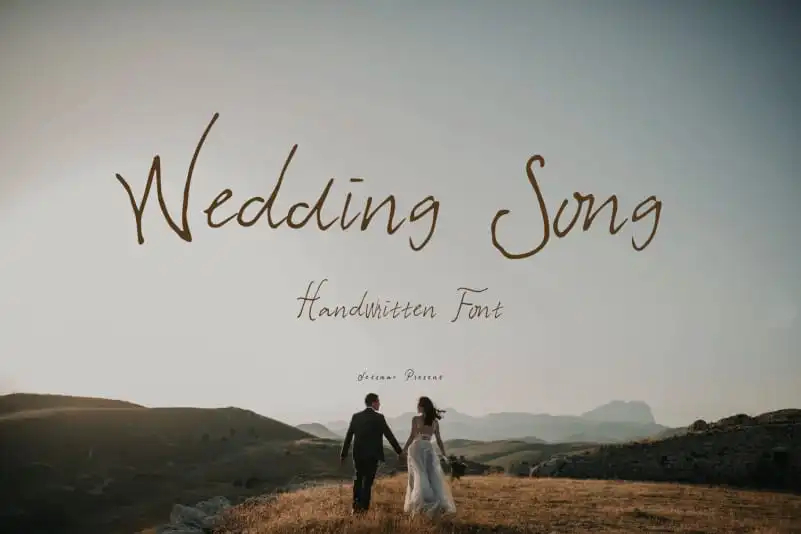
Wedding Song Handwritten Font – Download Grátis
A Wedding Song Handwritten Font é uma elegante fonte escrita à mão perfeita para quem quer capturar a atmosfera romântica de um casamento em seus projetos criativos. Essa fonte foi feita especificamente para adicionar um toque íntimo e sentimental, tornando seu trabalho ainda mais especial. Ideal para criar cartões de aniversário, selinhos do casamento ou até mesmo como uma fonte de decoração para sua sala de estar, a Wedding Song Handwritten Font é o elemento perfeito para aqueles que querem transmitir amor e emoções através dos textos. Esta font, criada pelo designer Jetsmax, oferece um toque delicado e autêntico à qualquer projeto, tornando-a uma opção versátil e encantadora na sua lista de recursos gráficos favoritos.